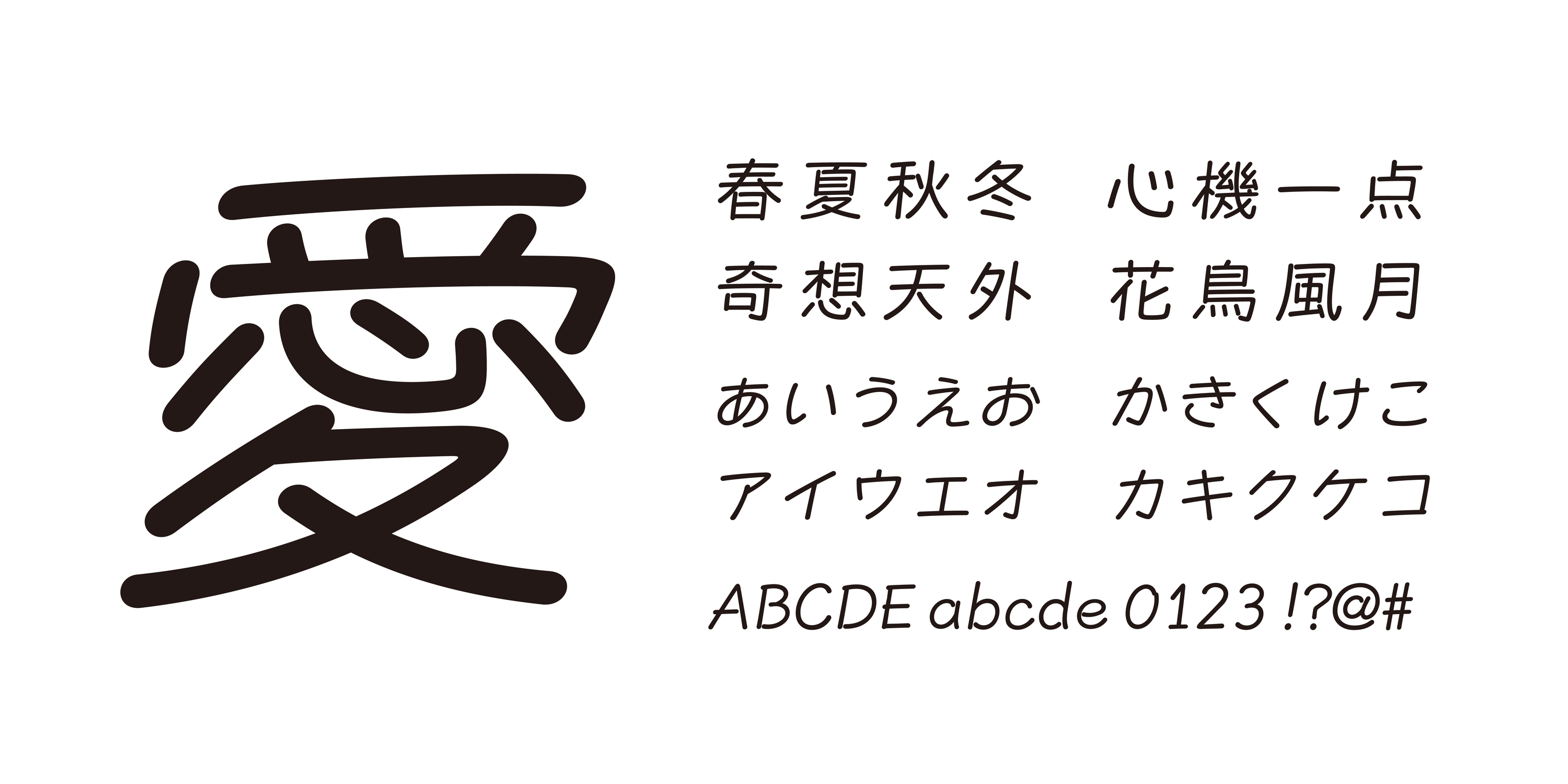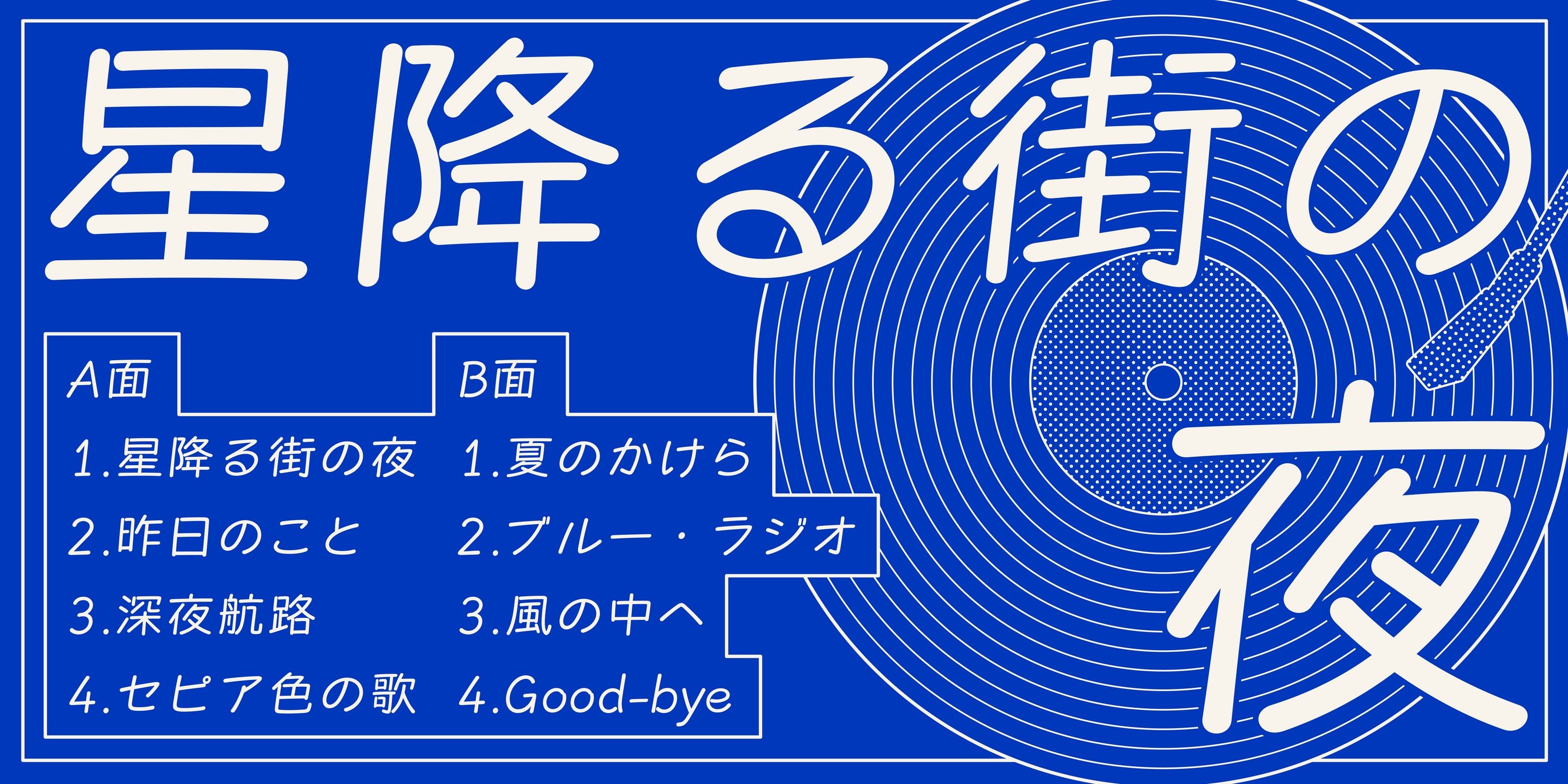
Monotype、新コンセプトフォント第2弾「せぴあチューン」をリリース
せぴあチューン
かつてのポップスやR&Bが、カーステレオから流れ出すような、懐かしさを感じさせる書体です。映画字幕などにおける歌唱シーンの表現に用いられるイタリック体に着想を得て、生まれました。
フェルトペンで一筆一筆書いたような手書きの風合いと、イタリック体が持つ独特のリズム感が、ノスタルジックな雰囲気を醸し出します。懐かしい思い出を呼び起こすような、特有の空気感が特長です。
昭和レトロなポスター、映画や音楽のタイトル、そして温もりを感じさせるパッケージデザインなど、レトロな世界観を表現するデザインに最適です。感情を込めて伝えたいメッセージや、親しみやすさ・優しさを表現したいシーンにも適しており、手書きの温かみと可読性の高さを両立。味わい深い表情を持つ書体として、幅広い用途にご活用いただけます。
| 書体名 | せぴあチューン |
| ウェイト | Regular |
| デザイナー | Monotype Studio |